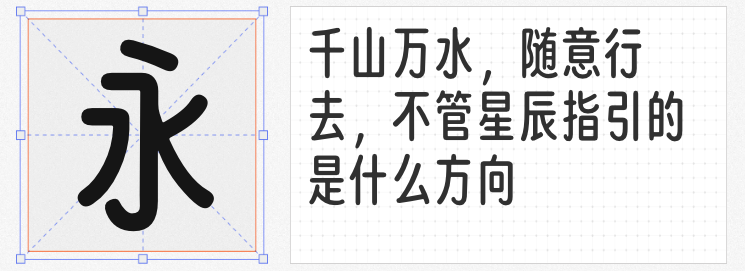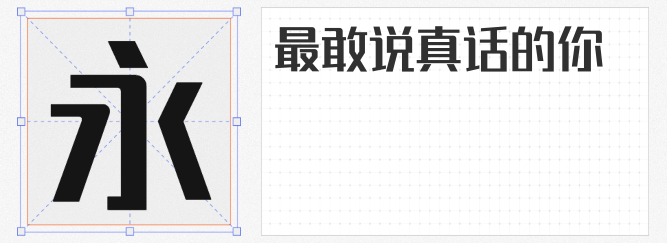
在海报设计同质化严重的当下,一款兼具个性与辨识度的免费商用字体,往往能成为突破视觉重围的利器。本文精选四款风格迥异的创意字体,涵盖力量感、现代感、文化感与亲和力,助力设计师打造令人过目难忘的海报作品。
一、锐字潮牌真言简2.0免费 准粗
这款字体以浑厚笔触构建视觉骨架,直角与圆角的错落搭配赋予字形动态平衡感。笔画转折处刚柔相济,既保留传统书法的遒劲,又通过简洁有序的落笔提升现代适用性。在运动品牌海报中,其力量感可强化品牌调性;在文化类海报中,端正凝练的形态又能传递庄重感,是平衡艺术性与实用性的理想选择。
二、阿里妈妈数黑体
阿里妈妈数黑体以饱满字型与现代布白构建视觉节奏,厚实简练的笔触中暗藏设计巧思。通过精准的“图形感”与“书写感”权衡,既保证远距离阅读的清晰度,又以特殊笔画处理营造先锋气质。科技产品发布会海报、潮流品牌宣传中,其醒目时尚的视觉语言能瞬间抓住观众眼球,成为信息传递的高效载体。
三、一品启航体
以传统书法为魂,融入昂扬向上的笔锋设计,这款字体既是企业精神的视觉化表达,更是文化传播的普惠工具。在公益海报中,其遒劲有力的字形可传递坚定信念;在文化展览海报中,书法底蕴又能唤起民族认同感。免费开放的商用政策,让这款承载正能量的字体成为连接社会价值的桥梁。
四、猫啃忘形圆
基于开源字体得意黑的圆化改造,这款字体以柔和曲线消解科技冰冷感,在保持辨识度的同时注入温暖气质。食品包装、儿童活动等需要拉近心理距离的海报场景中,其圆润形态可营造轻松氛围;在社交媒体传播中,独特的二创背景更能引发年轻群体共鸣。
这四款字体通过差异化设计语言,为海报设计提供多元表达可能。在版权风险日益受重视的今天,它们的免费商用属性更让创意无后顾之忧,助力设计师以专业姿态探索视觉表达的无限边界。